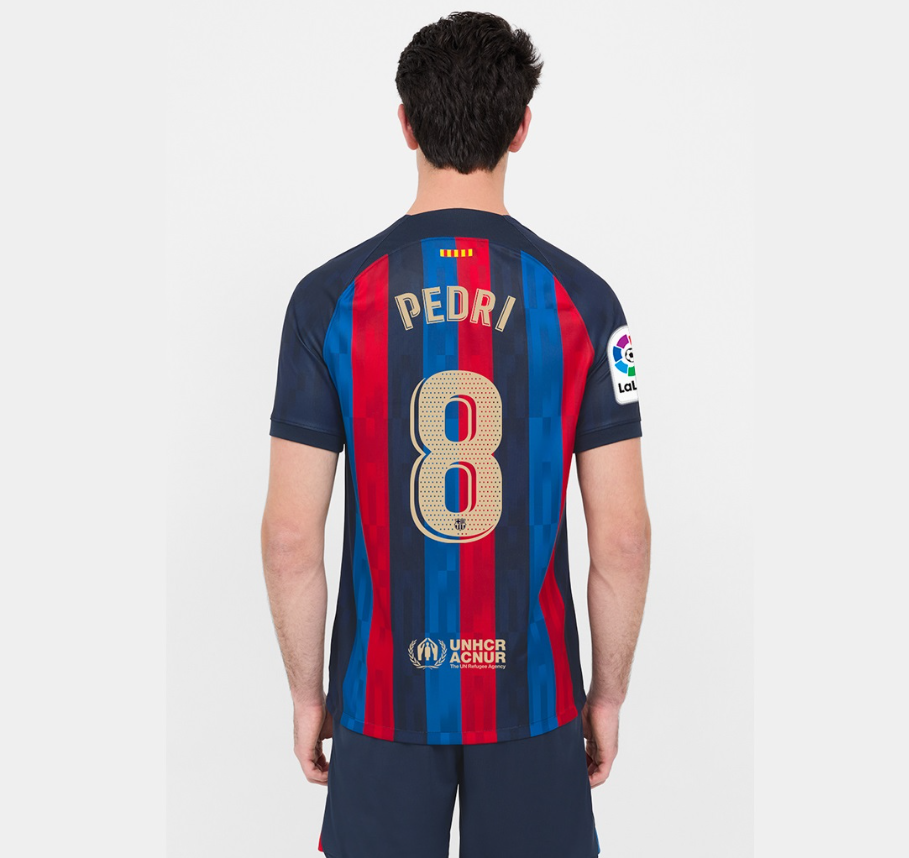
Fonte Barcelona – Temporadas 2019 a 2023 (UCL & Copas) – Download TTF
Quando falamos de identidade visual no futebol mundial, poucos clubes têm o peso do FC Barcelona. Entre 2019 e 2023, o clube catalão viveu diversas fases, desde a era final de Messi até a chegada de Lewandowski, sempre acompanhado pelos designs inovadores da Nike.
Este post traz algo especial: o pacote da tipografia utilizada exclusivamente nas competições de “Copas” (Champions League, Europa League e Copa del Rey). Diferente da fonte padronizada de La Liga, esta é a fonte proprietária do clube, carregando o verdadeiro DNA Blaugrana.
Estilo Visual: A Identidade Catalã
A tipografia personalizada do Barcelona para este período foge do padrão genérico. Ela é baseada na arquitetura de Barcelona e na geometria do escudo do clube.
O estilo visual apresenta cortes diagonais agressivos e uma estrutura ligeiramente condensada, o que permite que nomes longos se ajustem bem às costas da camisa. É a fonte que você viu brilhar nas noites de Champions League e que estampou as camisas de lendas e novas promessas. O design transmite modernidade sem perder a elegância clássica exigida pela torcida Culé.